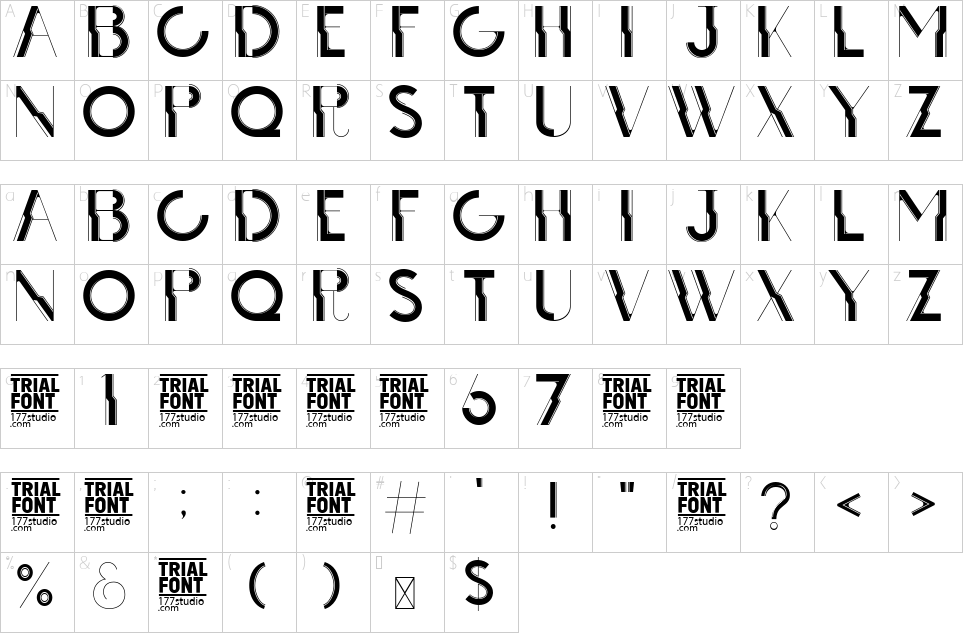
Descubra a fonte “Greatest Font”, uma escolha perfeita para aqueles que valorizam a elegância simples e o equilíbrio harmônico na tipografia. Criada pela equipe talentosa de 177Studio.com, esta fonte foi projetada com um design limpo que se adapta facilmente aos seus projetos de escritório pessoal ou corporativo. Com seu estilo minimalista e versátil, “Greatest Font” é uma opção ideal para quem busca uma fonte confiável e funcional sem perder a sofisticação. É impressionante ver o quanto esta fonte tem ganho em popularidade – já foi baixada mais de 1.518 vezes desde seu lançamento. Experimente “Greatest Font” hoje e adicione um toque diferenciado ao seu próximo projeto, sem gastar nenhum centavo.